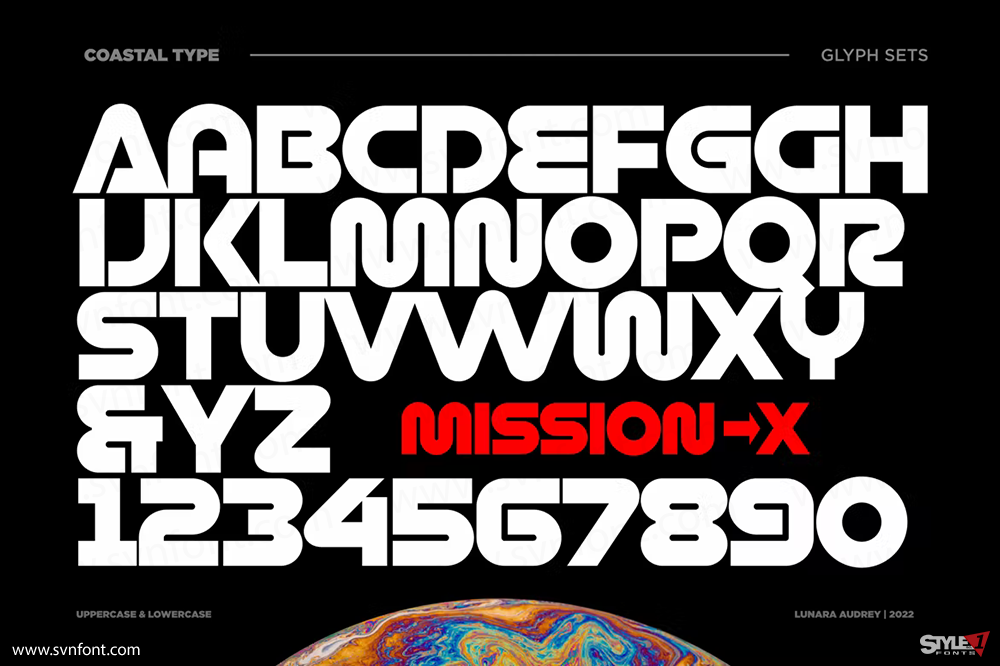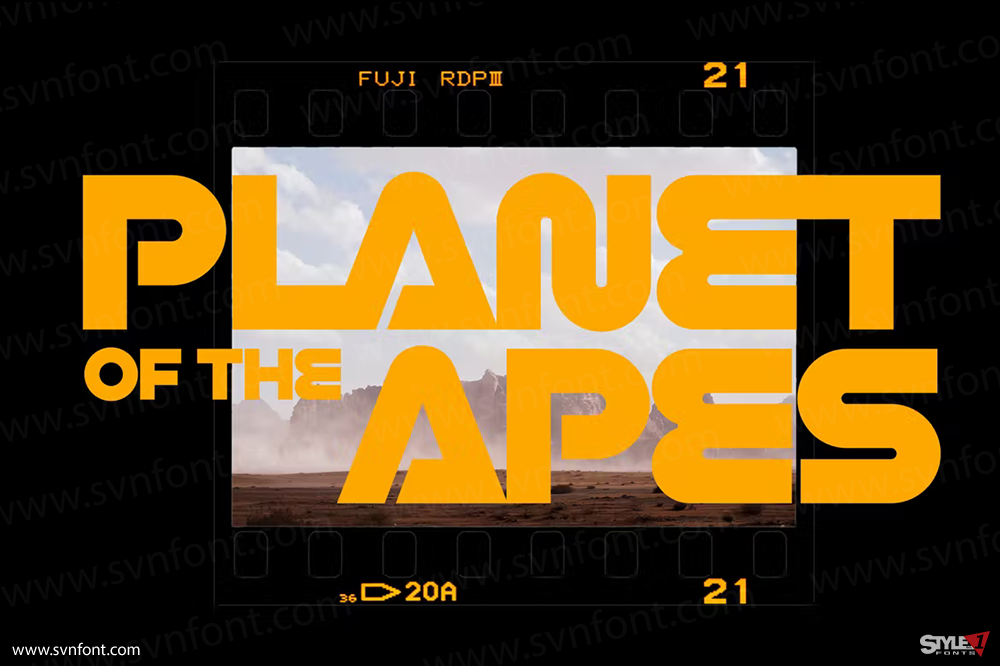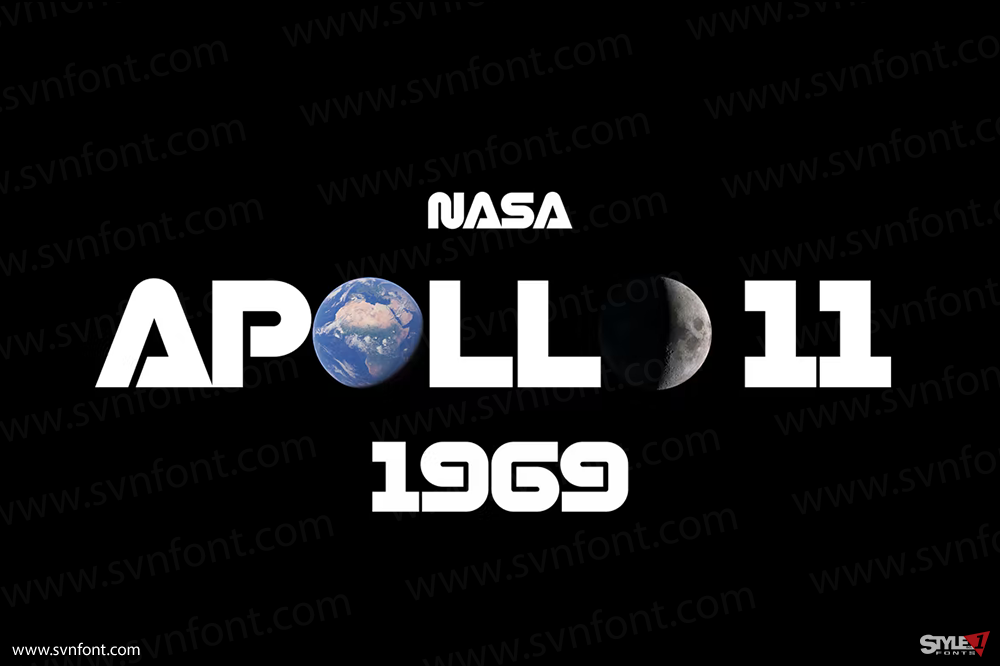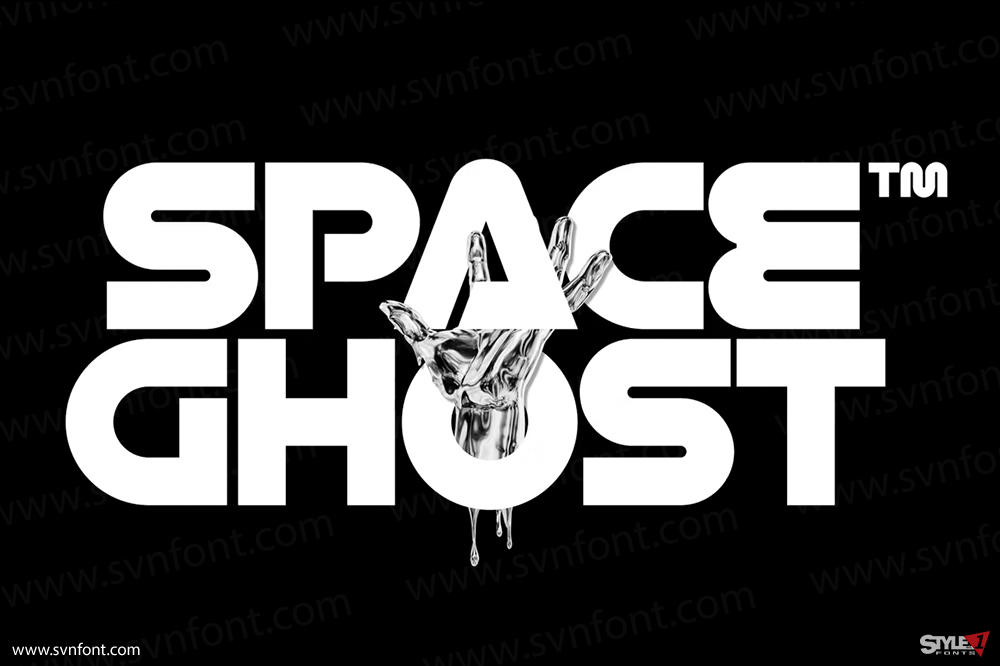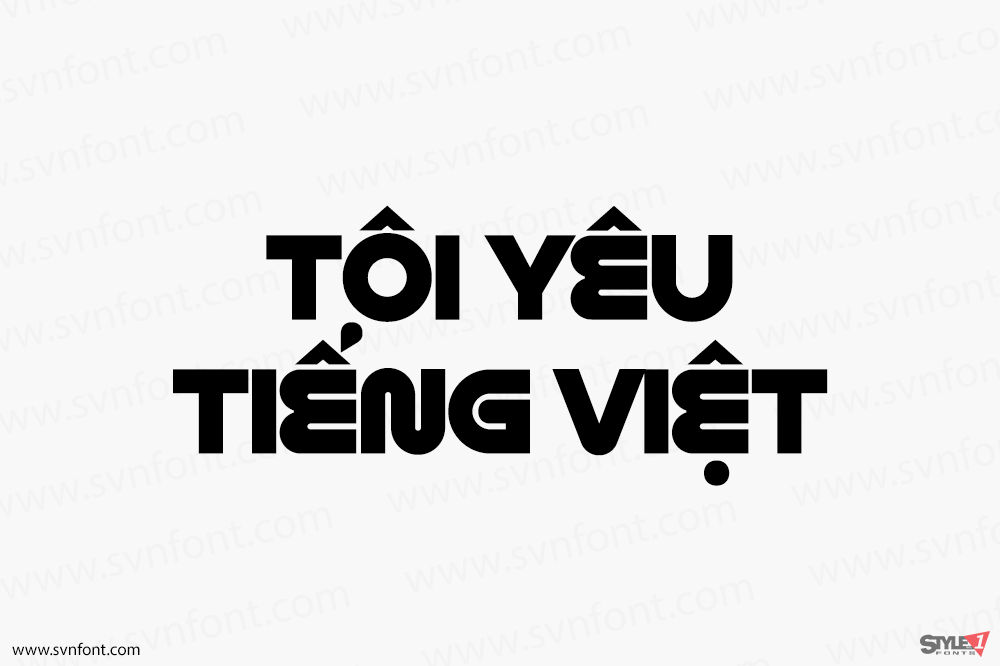
Mission X là một kiểu chữ sans serif siêu hiện đại. Font sans serif này được lấy cảm hứng từ tính thẩm mỹ của Stanley Kubrick, các bộ phim khoa học viễn tưởng và chủ đề không gian. Hãy sử dụng nó cho các thương hiệu có tầm nhìn xa hoặc các thiết kế mong muốn trở nên công nghệ cao, hiện đại và tương lai. Bạn là một đạo diễn phim khoa học viễn tưởng và đang tìm kiếm một sự thay thế cho font Eurostile không thể tránh khỏi? Giờ đây bạn đã có nó!
Nhà thiết kế: Lunara Audrey
Nhà phát hành: Coastal Type